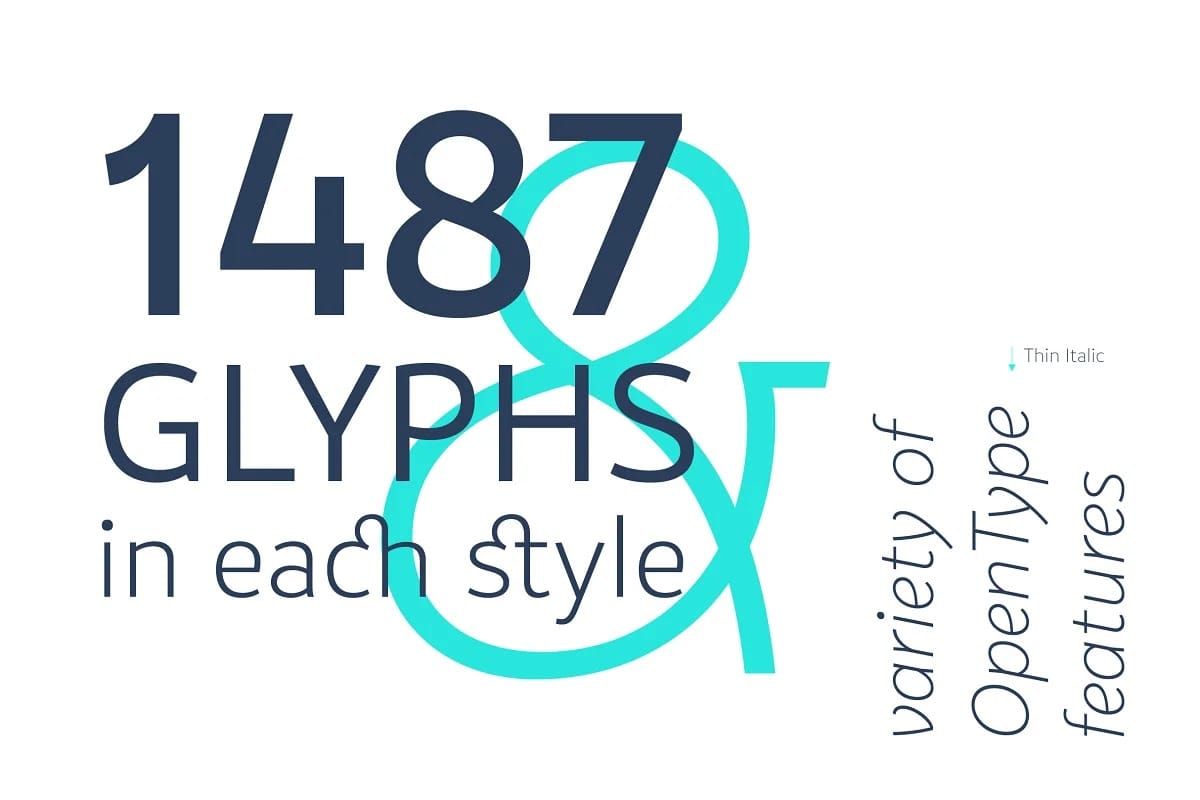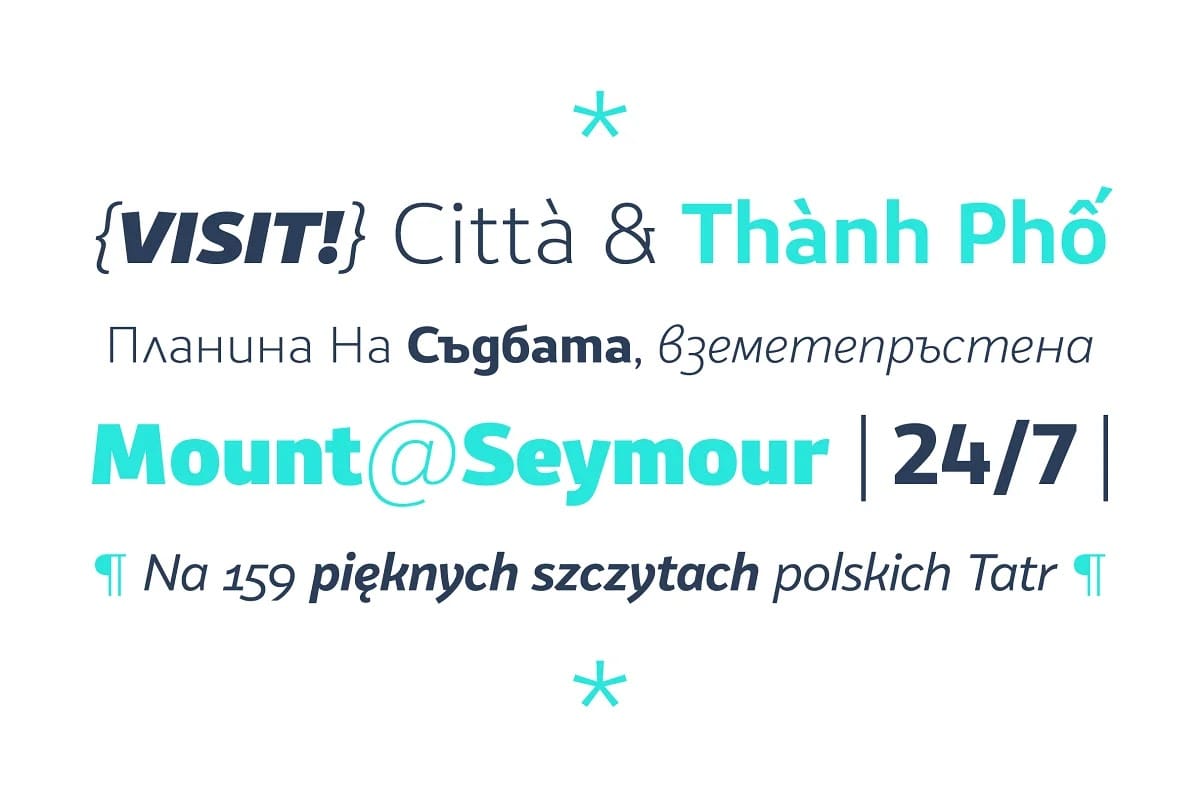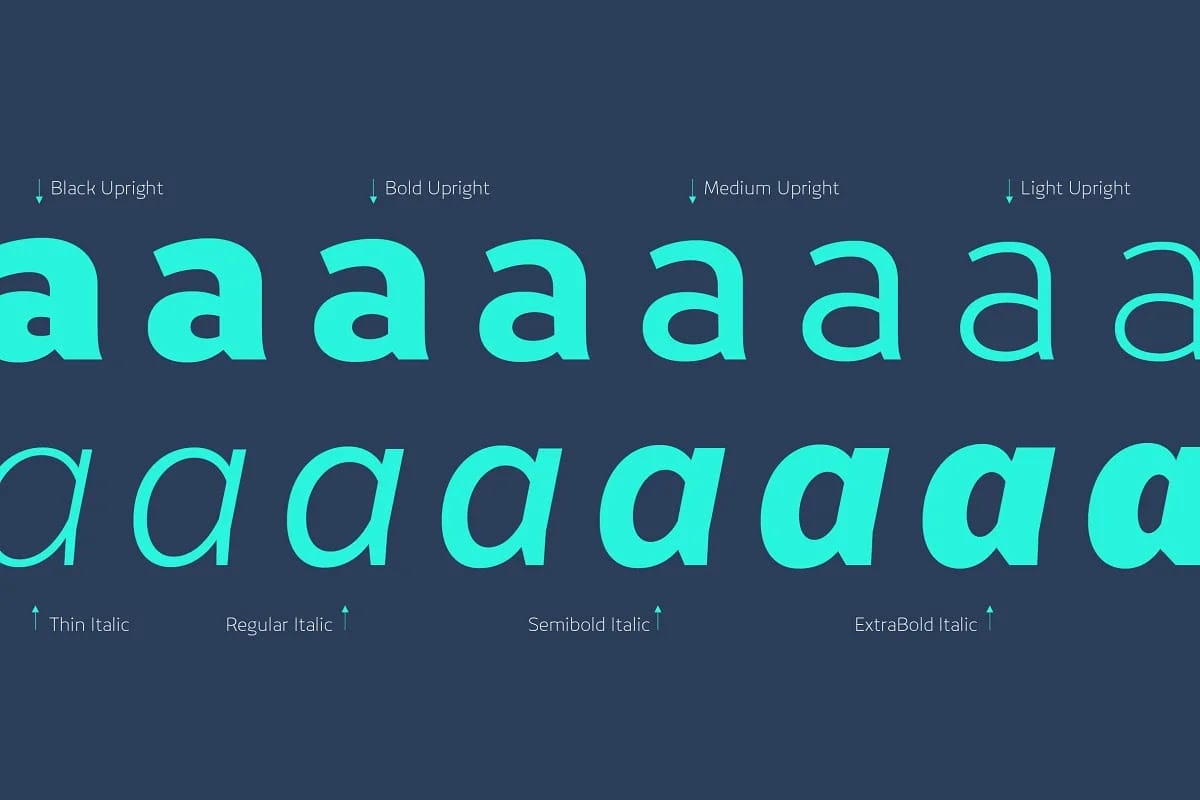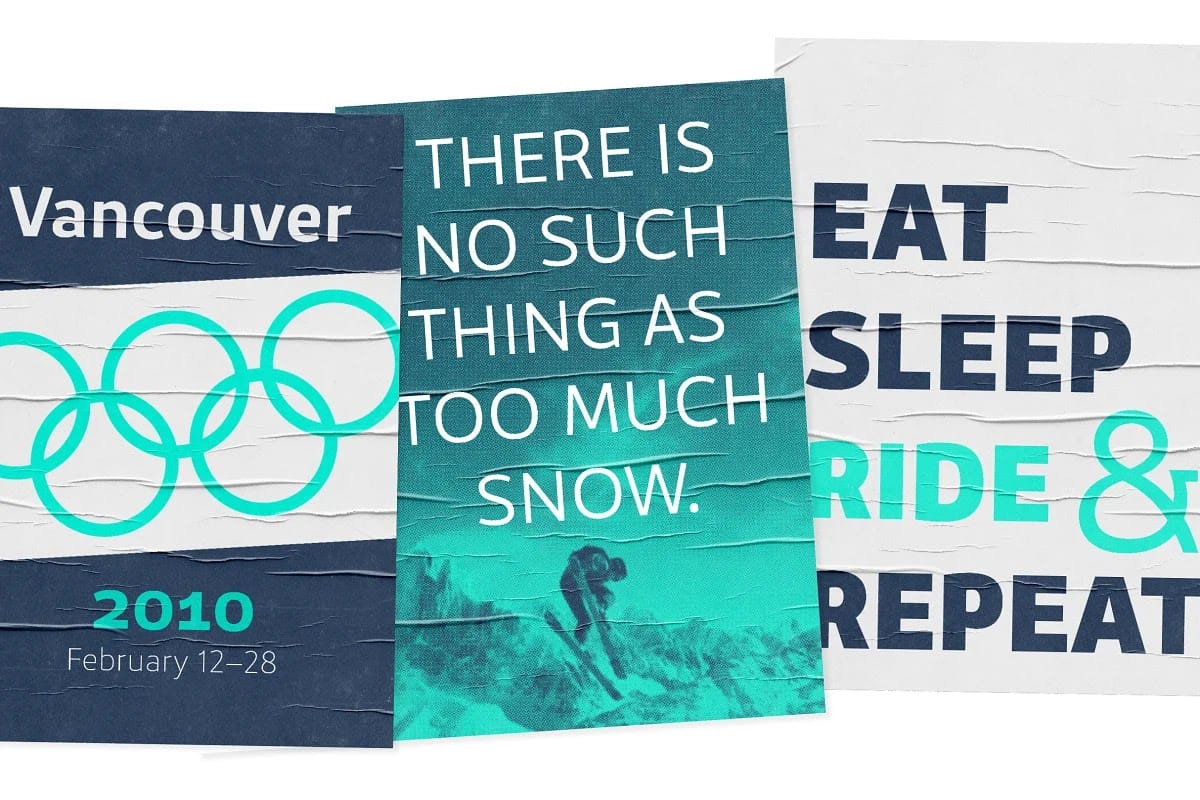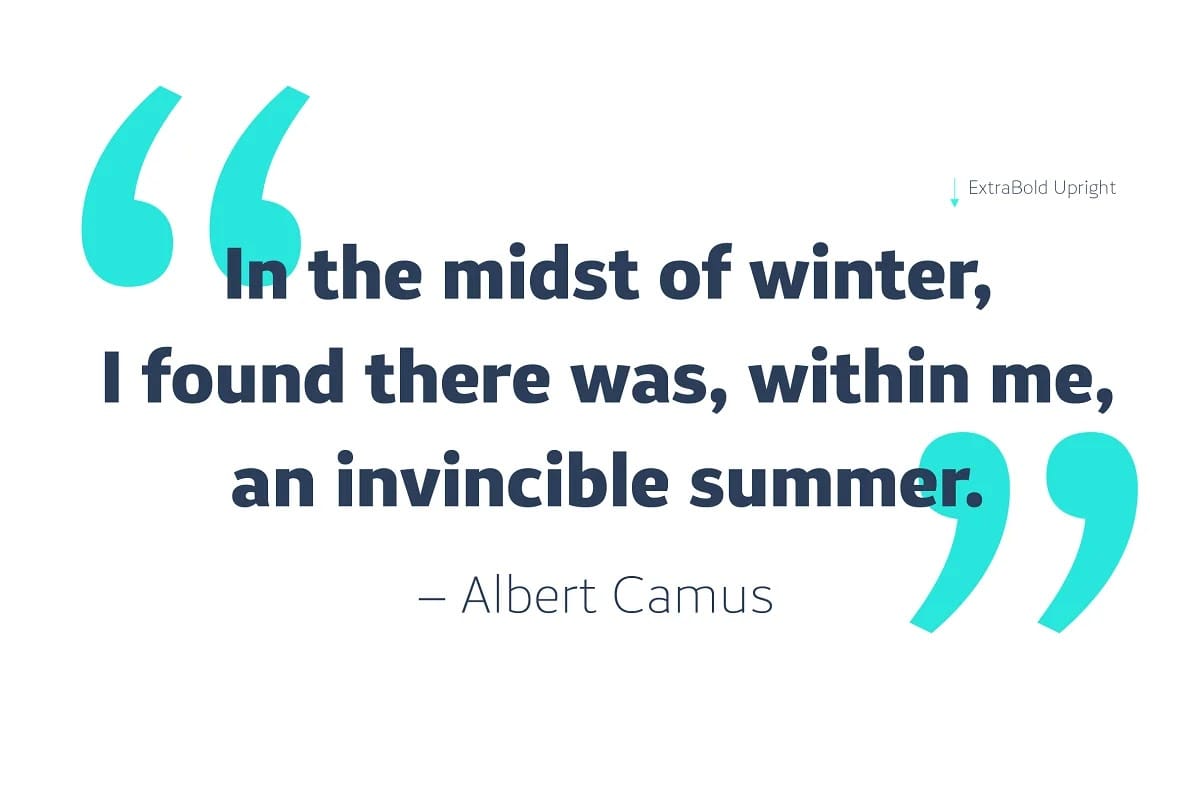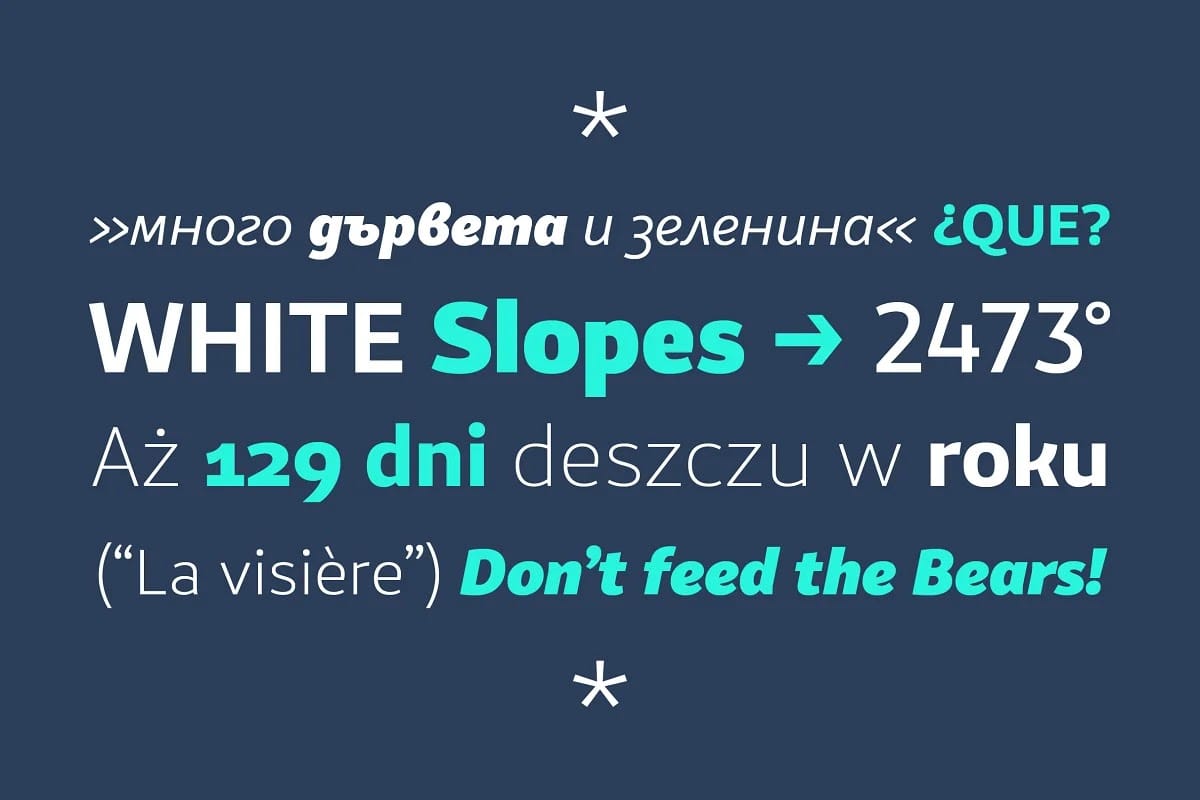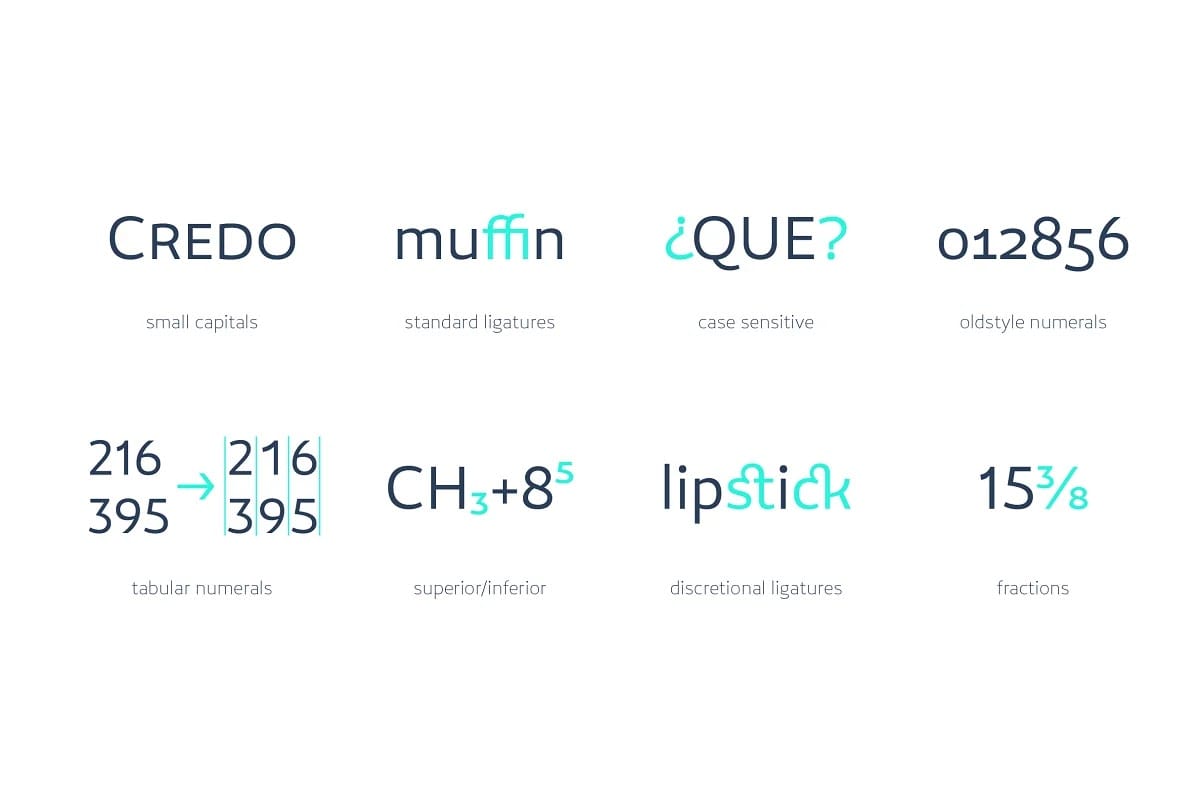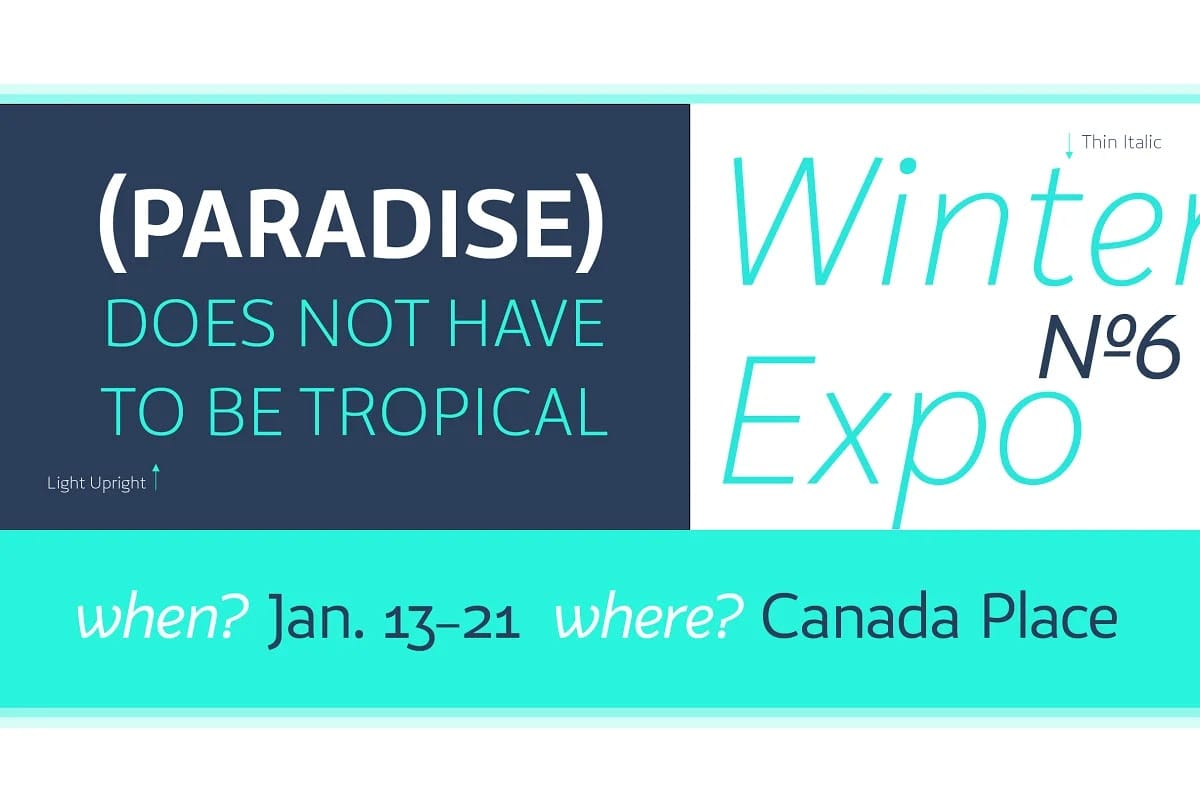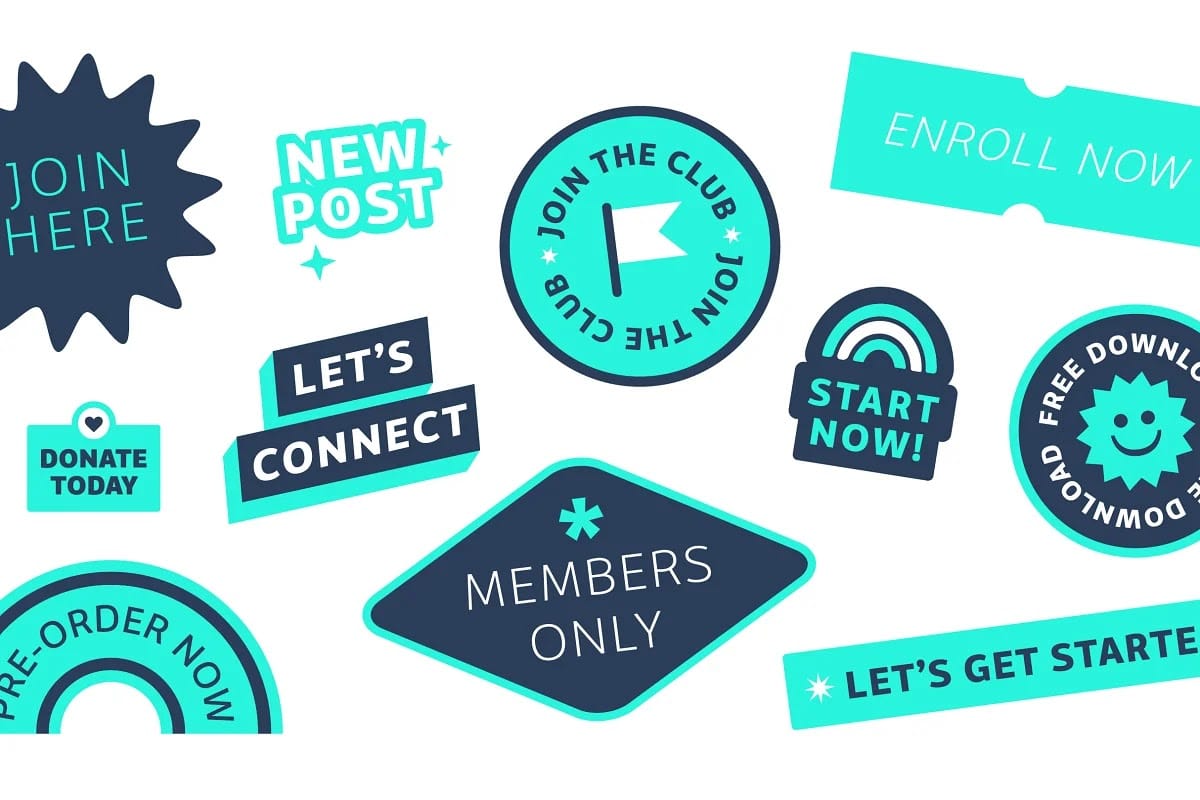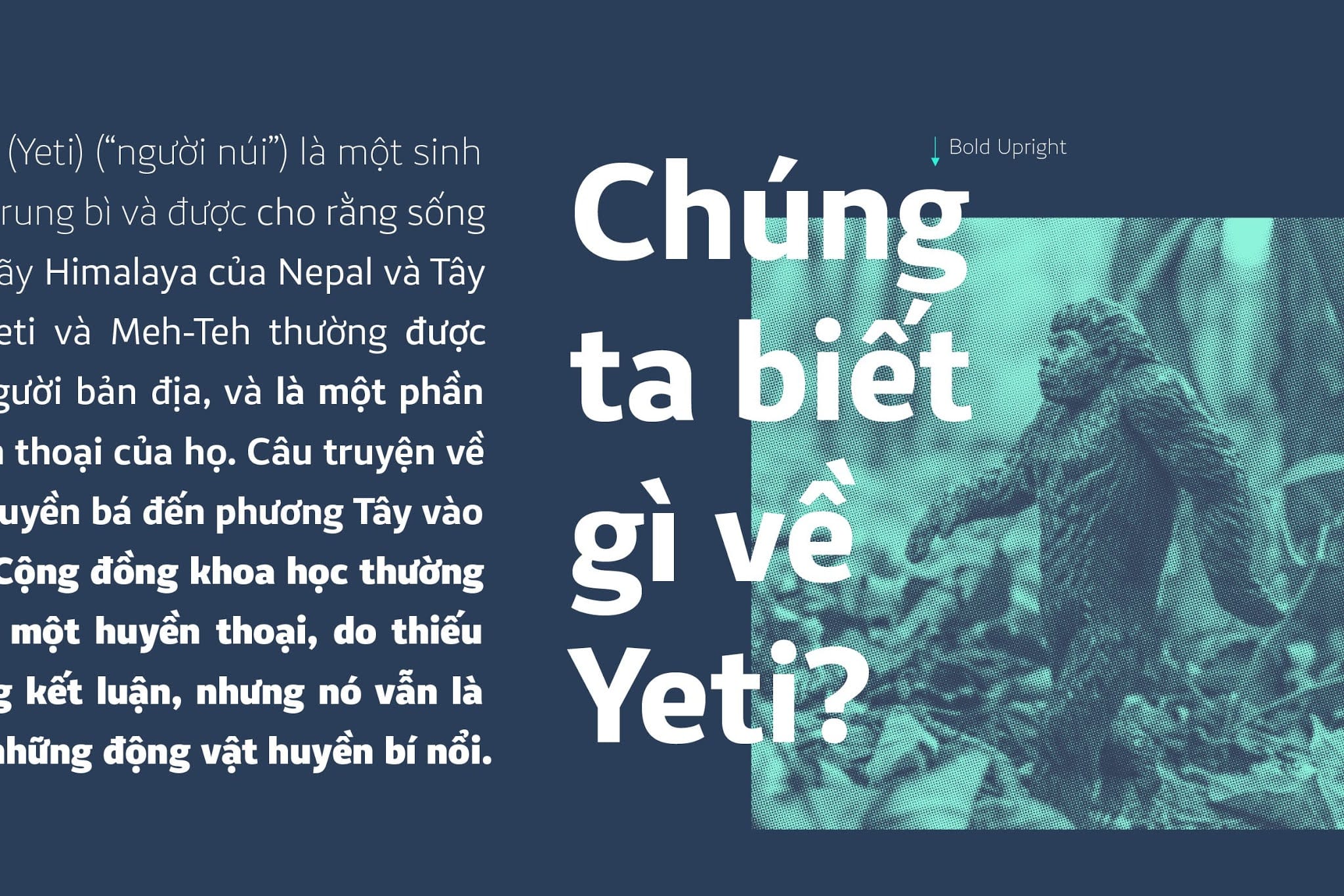
VanSans Type Family là một bộ font, được tạo ra để mang một tinh thần vui vẻ và ấm áp vào một thiết kế tối giản. Nó được lấy cảm hứng từ thành phố Vancouver, kết hợp cảm giác công nghiệp với sự thân thiện và cởi mở của người dân.
Với kích thước lớn, nó rõ ràng và dễ đọc trong cả môi trường in và màn hình. Được thiết kế để linh hoạt và thích ứng với bất kỳ hệ thống phân cấp kiểu chữ nào mà một nhà thiết kế sẽ cần. Với weight từ Thin đến Black, nó hỗ trợ cả chữ Latinh và Cyrillic mở rộng với nhiều tính năng OpenType.
VanSans hoạt động tốt nhất trong lĩnh vực biên tập, xây dựng thương hiệu web và quảng cáo.
Các tính năng của VanSans:
• Bộ đếm mở và có độ tương phản thấp
• Hơn 1400 chữ glyph trong 16 kiểu
• Tiếng Latinh mở rộng và chữ Kirin
• Hỗ trợ 219 ngôn ngữ dựa trên tiếng Latinh bao gồm cả tiếng Việt (Latinh Plus)
• Các tính năng của OpenType như: chữ hoa nhỏ, chữ ghép, số kiểu cũ, bảng số liệu, phân số, các dạng phân biệt chữ hoa chữ thường.